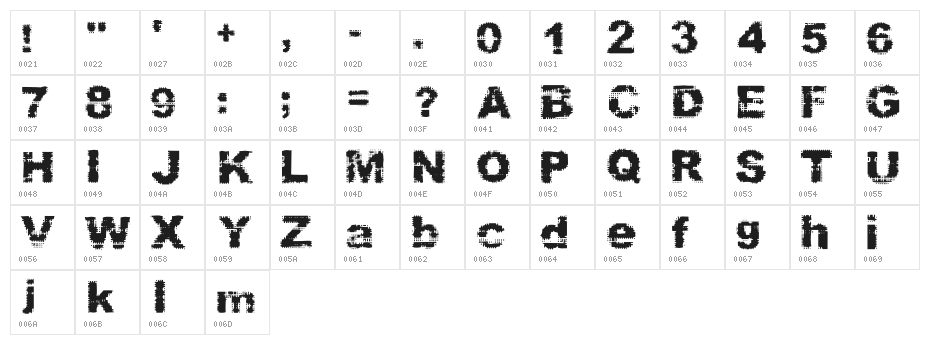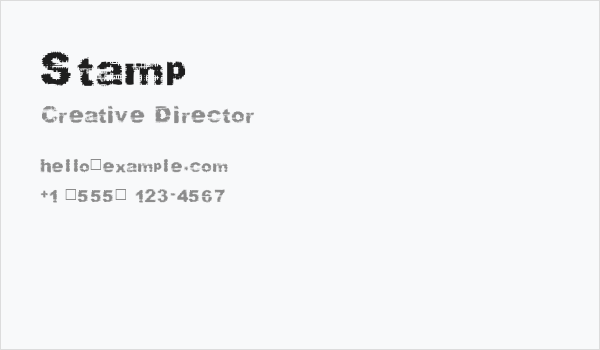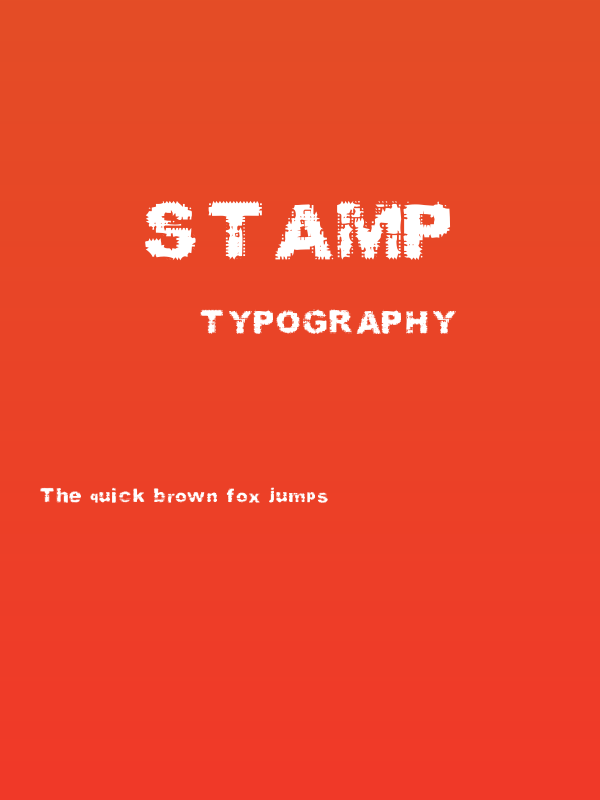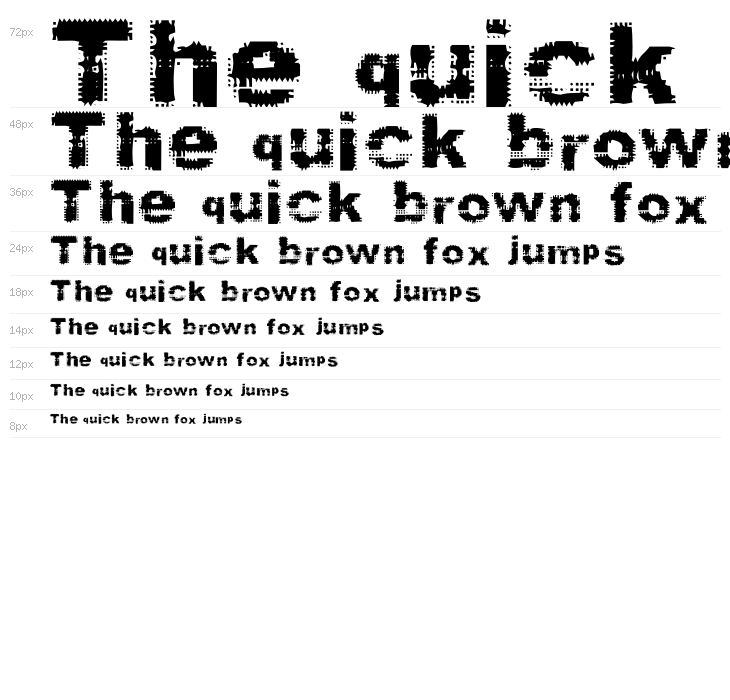
Stamp Font
| Название | Stamp |
| Категория | Broken |
| Общий стиль | Vintage |
| Рекомендуемые проекты | Ideal for posters, album covers, branding for edgy products, and any design needing a vintage, industrial look. |